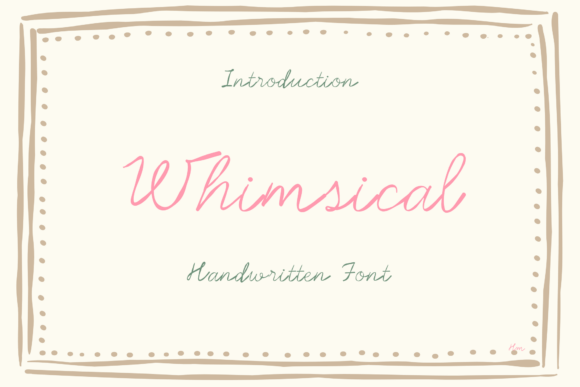
Whimsical
適切なデザイン要素を見つけるのは難しい場合がありますが、Whimsicalは作品を即座に引き立てる優れたコレクションを提供します。
精密に作られたWhimsicalは、クリーンなベクター、滑らかなタイポグラフィ、そして安心のための商用ライセンスを提供します。
POD(オンデマンド印刷)製品、結婚式の招待状、またはソーシャルメディアのグラフィックを作成している場合でも、Whimsicalは理想的です。